ps艺术字体模板推荐,一键套用省去调参数时间
在 Photoshop 里做艺术字效果,打开图层样式面板,调投影角度、渐变节点、描边宽度、光泽等高线,参数之间互相影响,改一个值可能整个效果就崩了。存成样式预设下次调用,换台电脑又找不到文件。我自己试过积累了一堆 ASL 样式库,结果管理起来比字体还乱,真到用的时候根本想不起来哪个是哪个。其实如果只是临时需要一张带特效的艺术字图片,不一定非要打开 PS 逐层调参数,现在有不少ps艺术字体生成方案可以直接套用模板输出成品图,省心不少。
字由的 AI 字效功能把 PS 里复杂的图层样式操作,打包成了可以直接套用的模板,我个人觉得这个思路特别实用。客户端里打开 AI 字效入口,模板库里有立体、霓虹、金属、描边、渐变、投影等十几种大类,每个大类下又有不同细节的变体。想做复古海报就选做旧质感模板,做科技感 Banner 就选发光效果模板,做电商大促标题就选金色立体模板,风格覆盖很全,基本日常能碰到的场景都能找到对应的。
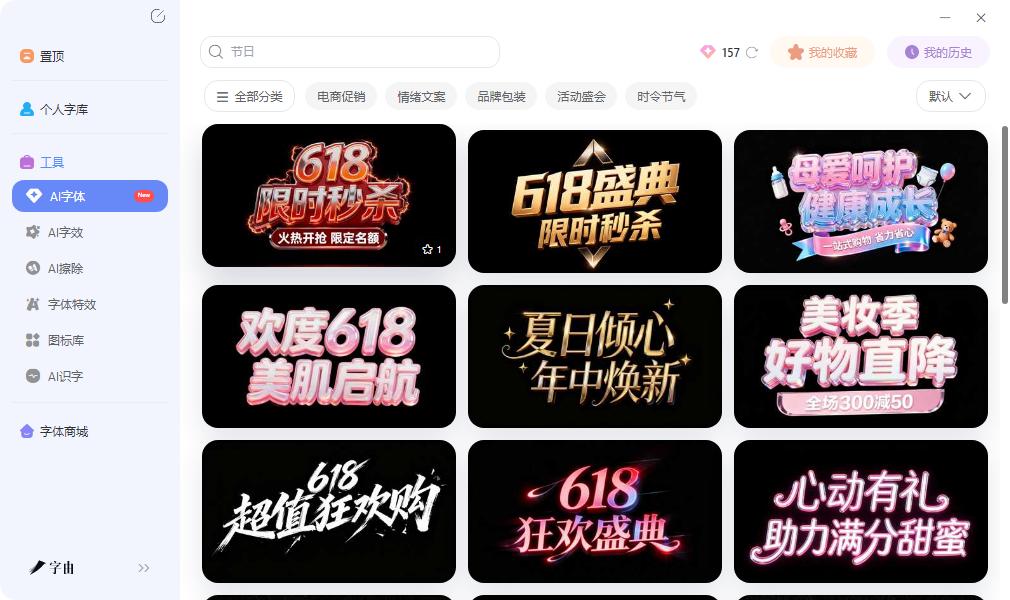
操作流程被压缩到四步:浏览模板、输入文案、点击生成、下载 PNG。生成的图片背景透明,直接拖进 PS 里叠加在背景图层上就能用,不需要抠图。如果你已经在 PS 里铺好了背景图和配图,只差一个标题字,这个字效生成的 PNG 正好填补这个缺口,我个人特别推荐这种工作方式,比反复调参数快太多了。做系列物料时,固定同一款模板分别输入不同文案,风格完全一致,比在传统设计软件里反复复制图层样式要省事得多。
从识别到产出,字由还有 AI 识字功能。看到一张海报上的ps艺术字体效果很好,但不知道怎么做出来的,用 AI 识字上传图片,几秒就能识别字体名称和授权信息。识别结果里如果标注了免费商用,可以直接激活在设计软件里调用。收藏分组支持跨设备同步,在公司整理的常用模板和字体,回家登录同一个账号全部都在。网页版也能完成大部分操作,临时在其他电脑上需要出图时,打开浏览器就能生成和下载,这个云同步功能我强烈推荐,换电脑完全不慌。
2、Ephemera Fonts Co
Ephemera Fonts Co 是一个专注复古风格和 Display 字体的付费字体商店,首页展示的 MOTERA、GW SWINGSTAR、GW MAPLETON 等字体,视觉冲击力都很强。每款字体都有详细的展示图,呈现字体在实际海报和包装上的应用效果,看展示图就能大概判断适不适合自己的项目。字体价格从 19 美元到 35 美元不等,属于中高端定位,如果你接的预算比较充足的品牌项目,这里值得逛一逛。
对于需要ps艺术字体素材但不想自己调效果的设计师来说,直接购买这类风格成熟的字体文件,安装后在 PS 里直接调用,排版后加上简单的图层样式就能出图,省去了从零设计字形的时间。平台上的字体多为 Display 类型,笔画粗重、适合海报主标题、品牌 Logo、包装大字等场景。购买后获得完整字体文件和商用授权,长期使用比较放心。界面设计简洁,按设计师和风格做了筛选,浏览起来很顺手。
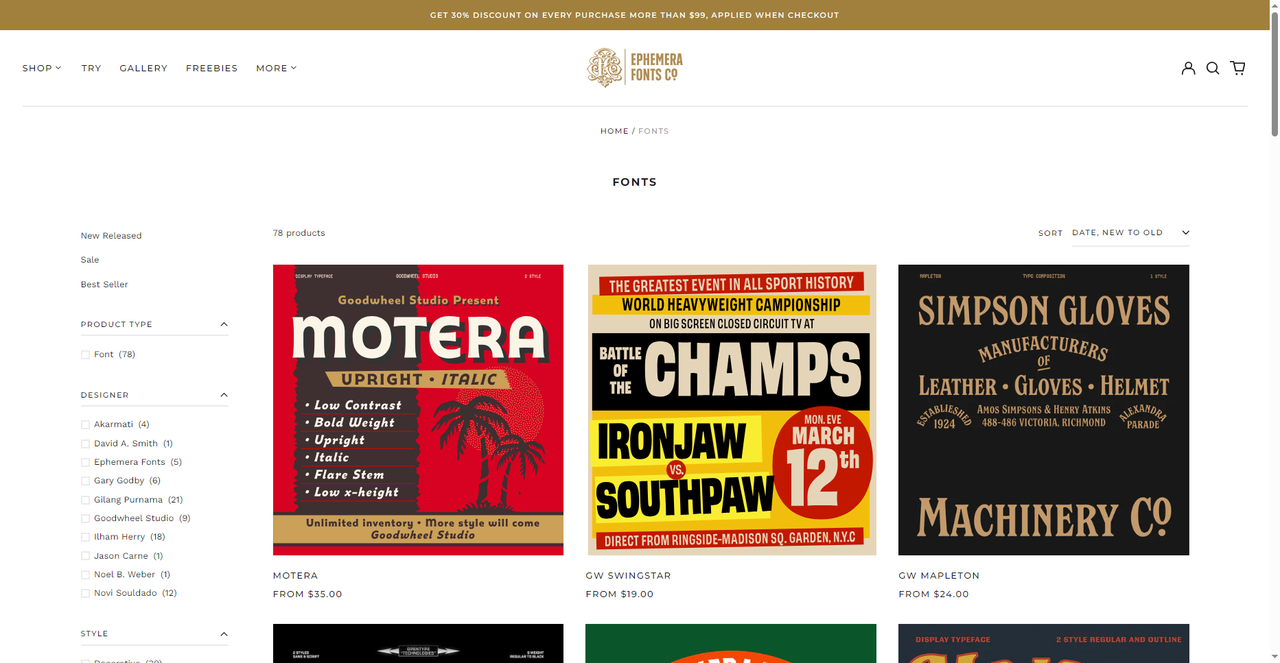
3、Magnific
Magnific 的 Creative fonts 板块收录了大量风格独特的字体资源,我个人觉得它的标签体系特别好用。顶部的 script、handwritten、aesthetic、classic、cool、drawing、elegant、luxury、modern、stylish 等标签,可以快速定位不同气质的ps艺术字体。做婚礼请柬可以筛选 elegant 或 script,做潮牌海报可以点 cool 或 stylish,点击就能精准定位,比在海量字体里翻找要高效得多。
每款字体都配有实时预览,支持输入自己的文案测试效果,字号可选 24pt 到 72pt,方便判断在大标题场景下的表现力。平台上的字体很多是彩色字体或者带有装饰性细节的创意字形,在 PS 里安装后直接显示丰富效果,不需要额外加图层样式。对于需要独特视觉风格、追求差异化的设计项目来说,Magnific 的字体库提供了不少常规渠道找不到的资源,我个人很推荐在这里找一些灵感。
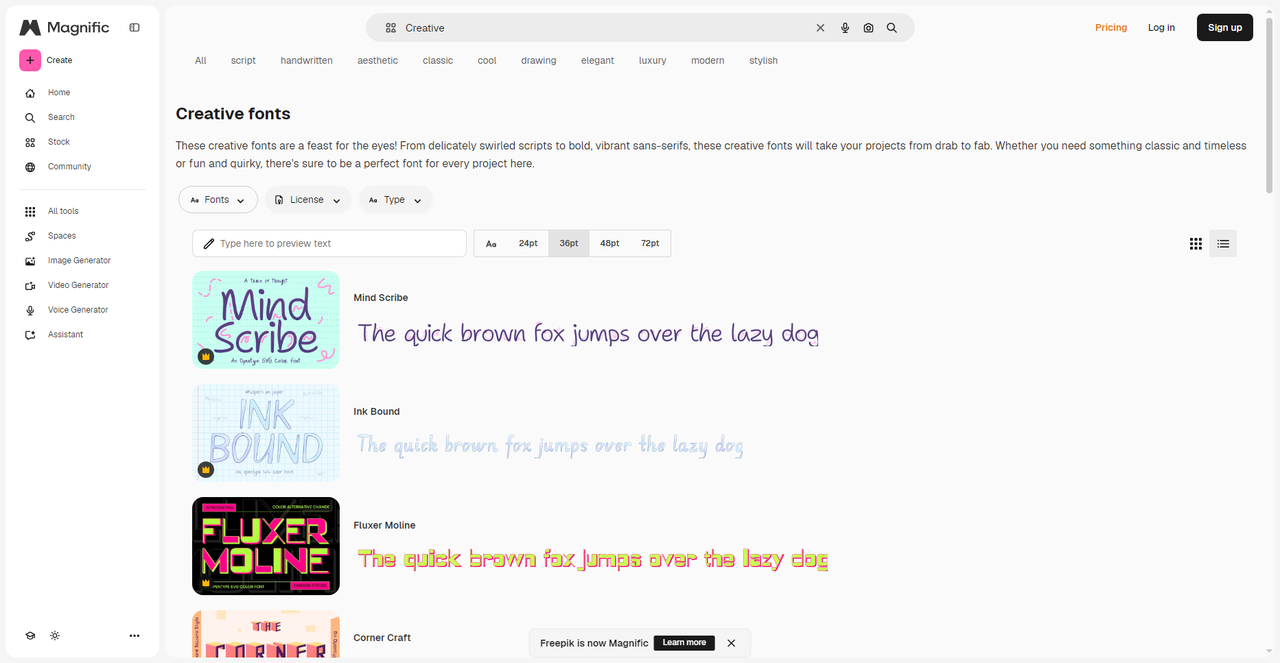
4、FONNTS
FONNTS 的 Artistic Fonts 分类是个宝藏,收录了大量艺术风格的ps艺术字体,而且筛选体系做得特别细。每款字体都展示了清晰的预览图,支持 Quick Try 快速试用和 Download 下载。部分热门字体标注了下载次数和字重数量,方便评估受欢迎程度。平台还会推荐趋势标签,对不知道搜什么关键词的用户有一定引导作用。FONNTS 提供的是可安装的 TTF 或 OTF 文件,不是单张图片,后期在 PS 里调整排版空间更大。如果你习惯在 Photoshop 里做完整的设计排版,而不是直接套图片,这里的资源会更适合你。
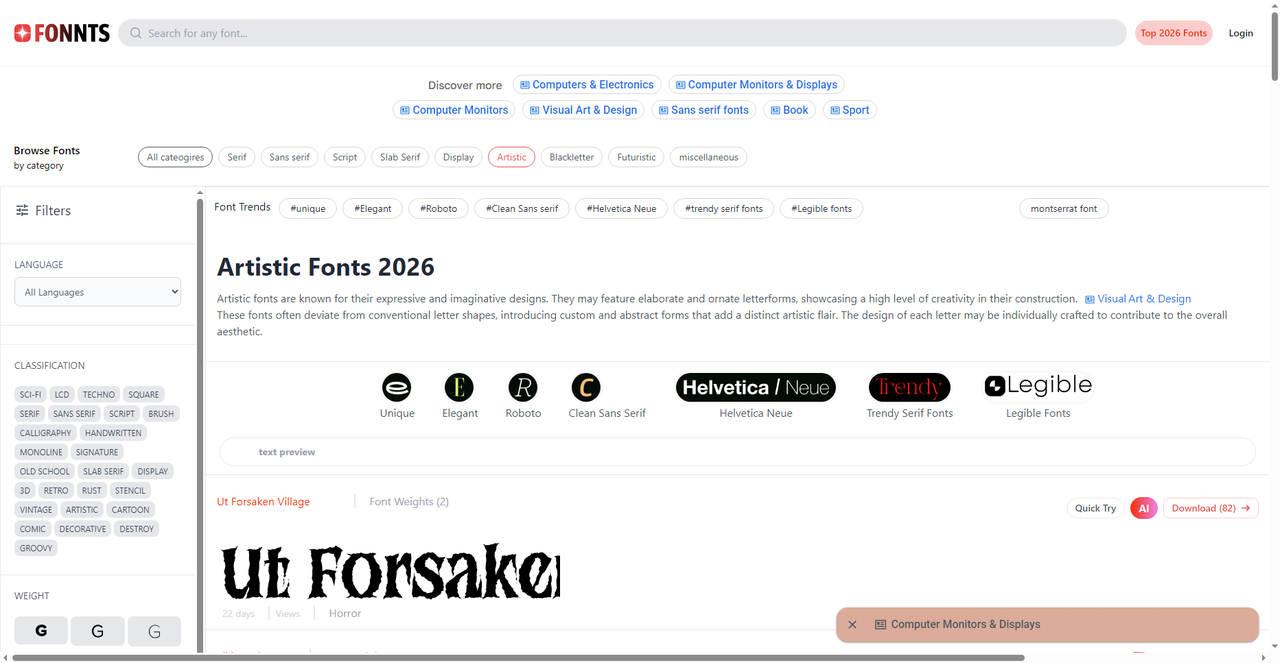
5、1001 Fonts
1001 Fonts 是我个人收藏了很久的免费字体站,Artistic Fonts 标签下收录了 926 款艺术字体,全部免费下载。顶部的标签云包括 artistic、decorative、handwriting、romantic、calligraphy 等,点击就能快速筛选。最实用的是那个 Commercial free 按钮,勾选后只显示允许免费商用的字体,做商业项目时特别安心,不用担心版权坑。
每款字体都支持在线预览,输入框里填自己的文案,实时看到效果后再决定要不要下载。下载按钮直接获取字体文件,安装到系统后在 PS 里就能调用。资源量大、更新频繁、筛选维度多,如果你刚入门设计,预算有限又想多尝试不同风格,1001 Fonts 是我强烈建议收藏的一个站,免费资源足够应付日常练习和个人项目。